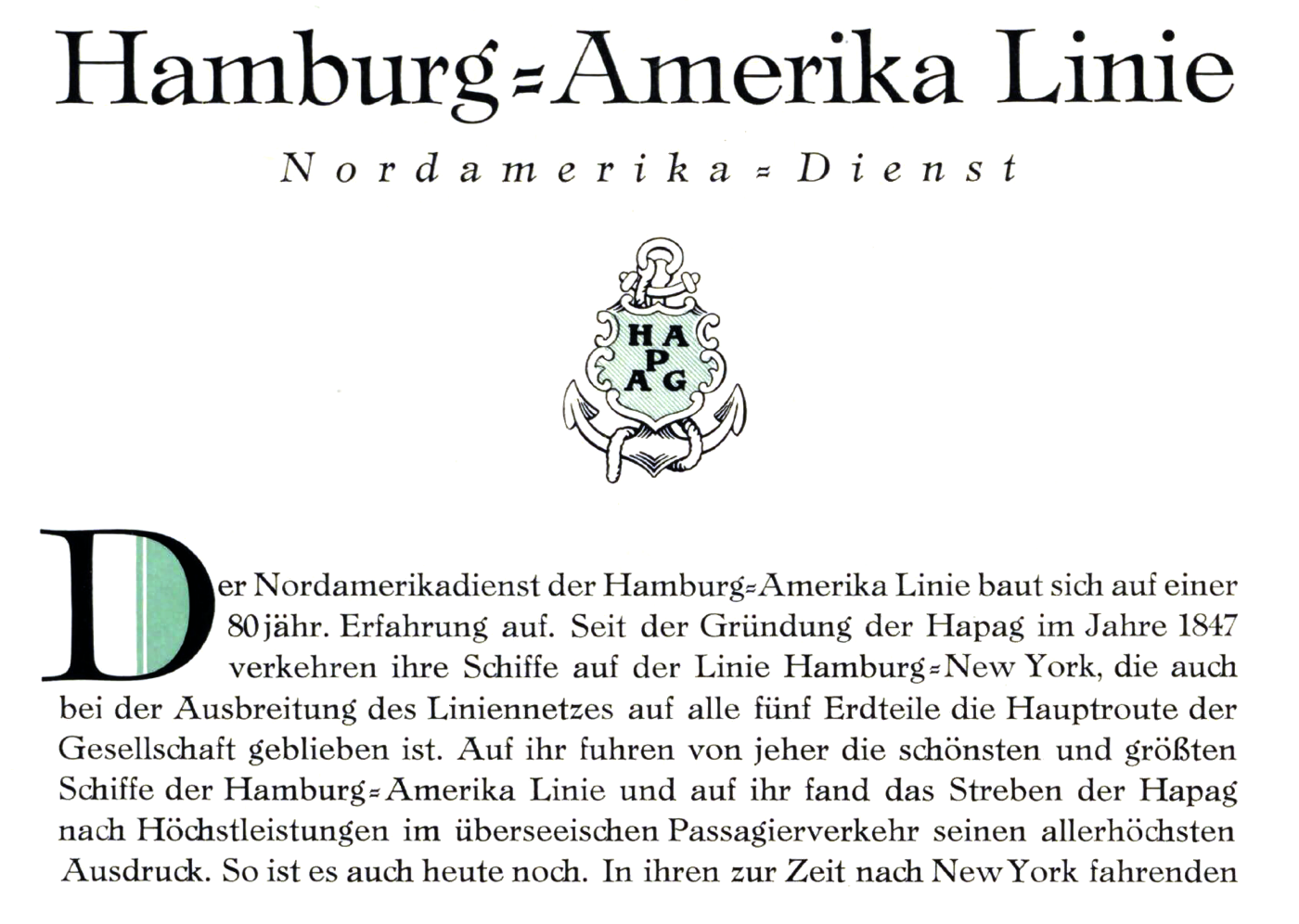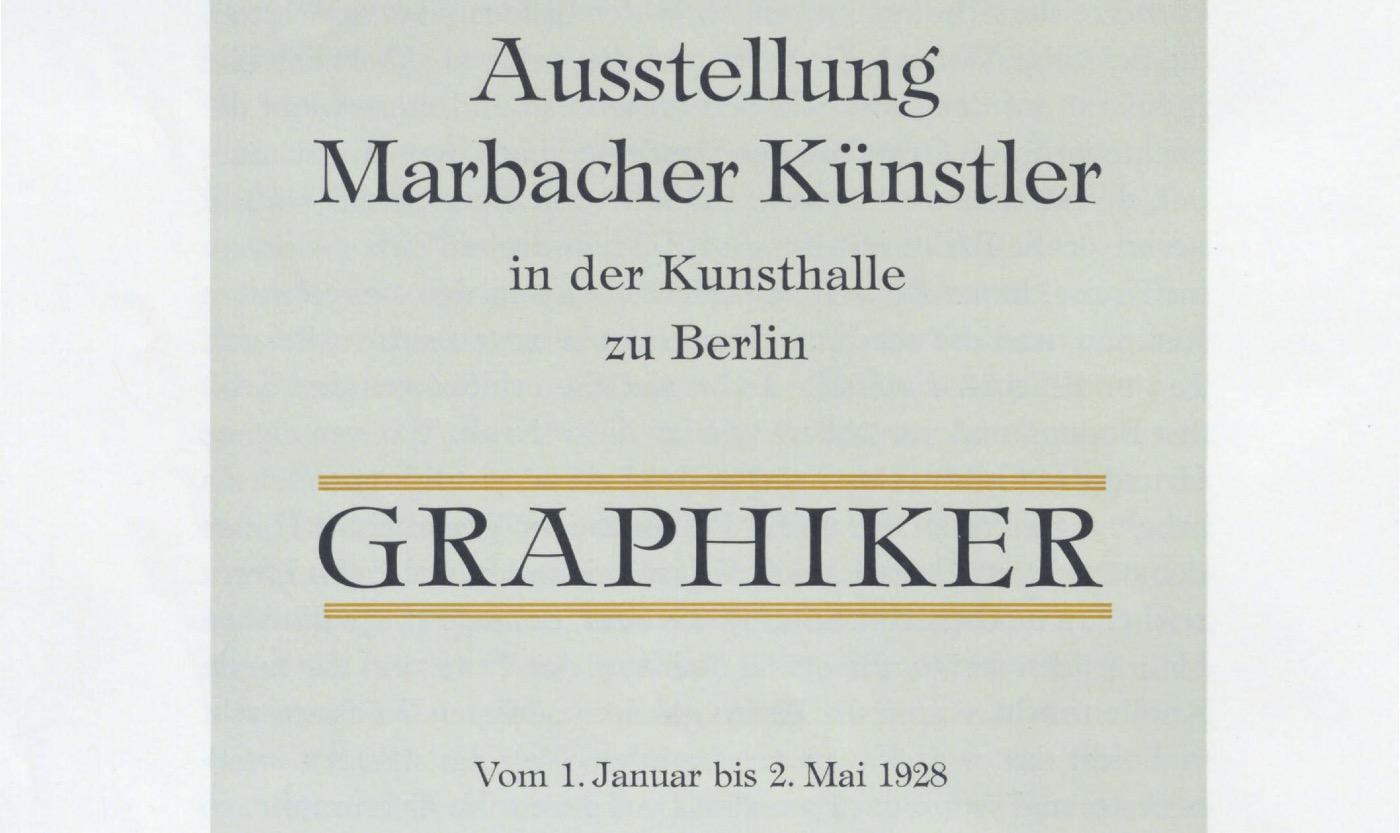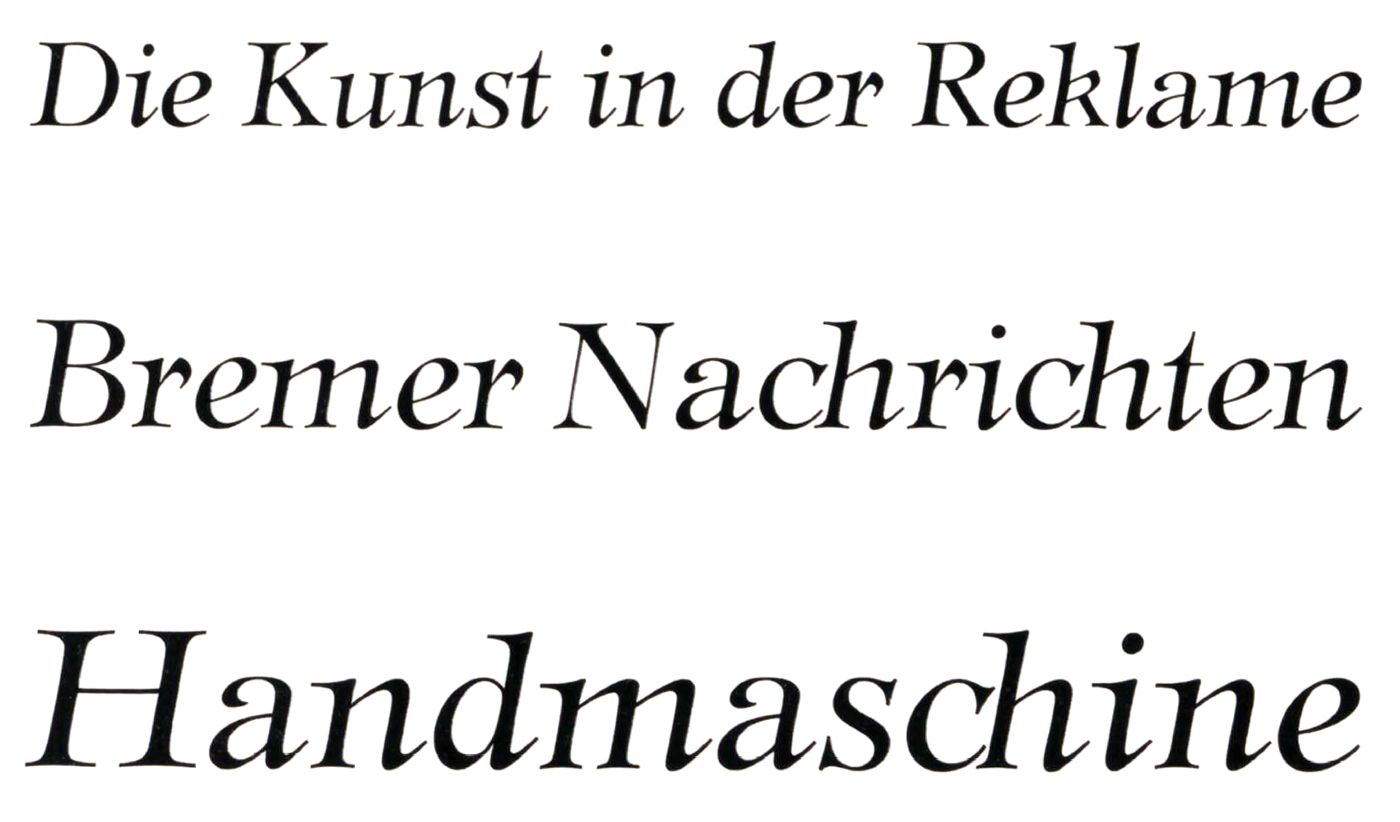
Font-Wiki: Trennert-Antiqua
Die Trennert-Antiqua von Friedrich Bauer erschien 1926 in mager und kursiv und wurde in der Folge auf sechs Schnitte (mager, kursiv, halbfett, fett, schmalhalbfett und kursiv fett) ausgebaut.
Eine Digitalisierung über Forgotten Shapes wurde angekündigt, ist aber bislang nicht erschienen.